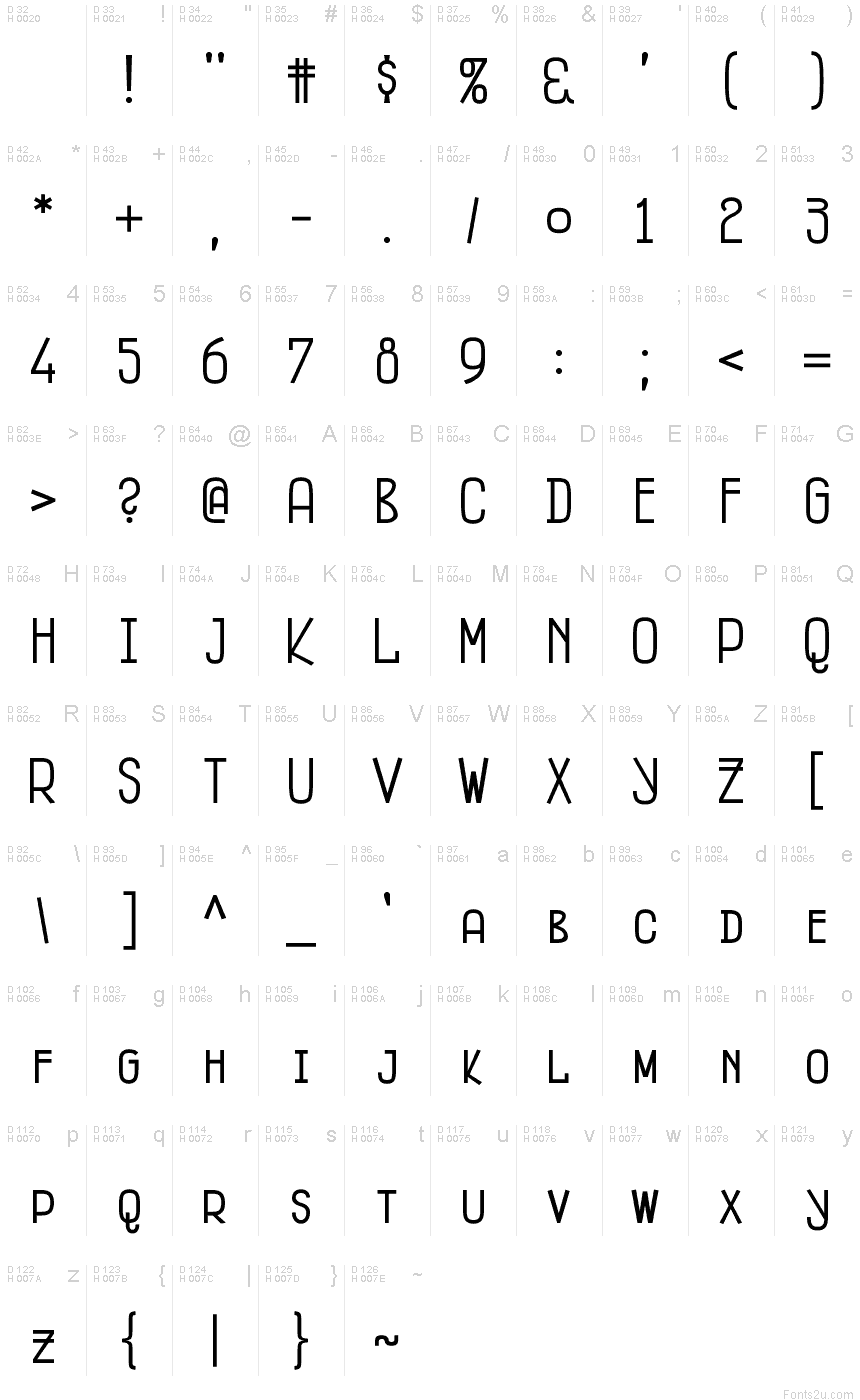
Fitzgerald フォント
Fitzgerald
Starving-4 Entertainmentによる「Fitzgerald」は、スリムで建築的な美学を持つ無料のレトロなディスプレイフォントです。背が高く角ばったフォルムとタイトな曲線は、まるでアールデコの看板と初期のコンピュータフォントを掛け合わせたような、夜のジャズクラブの洗練されたエネルギーを言葉に吹き込みます。ストロークはシャープで直立しており、独特のリズムがありながらも、大きなサイズでもしっかりと視認性を保ちます。
Fitzgeraldを使うと、見出しはクールで機械的な自信を持って収まります。ヴィンテージポスター、バーやスピークイージーのブランディング、書籍やZINEの表紙、アルバムアート、イベントフライヤー、モーショングラフィックスのタイトルに最適です。この無料フォントは、余白を活かすことで真価を発揮します。大きく配置し、本文にはシンプルでニュートラルなサンセリフ体を組み合わせれば、そのレトロな個性が存分に引き立ちます。